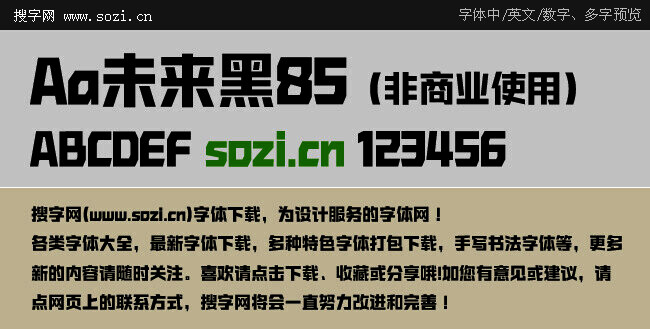
Aa未來(lái)黑85
搜字網(wǎng)給大家提供一款A(yù)a未來(lái)黑85(非商業(yè)使用)中文字體下載,該字體是一款藝術(shù)黑體,字體筆畫(huà)粗細(xì)一致,運(yùn)筆自然流暢,結(jié)構(gòu)清晰易識(shí)讀,以簡(jiǎn)單斜切的筆畫(huà)和方正飽滿的結(jié)構(gòu),來(lái)體現(xiàn)機(jī)械冷靜卻充滿力量的科技感,適合書(shū)裝設(shè)計(jì)、包裝、海報(bào)設(shè)計(jì)等應(yīng)用(此字體為個(gè)人非商用版,商用可以聯(lián)系QQ:1006760504)。
• 風(fēng)格類別: 現(xiàn)代藝術(shù)體